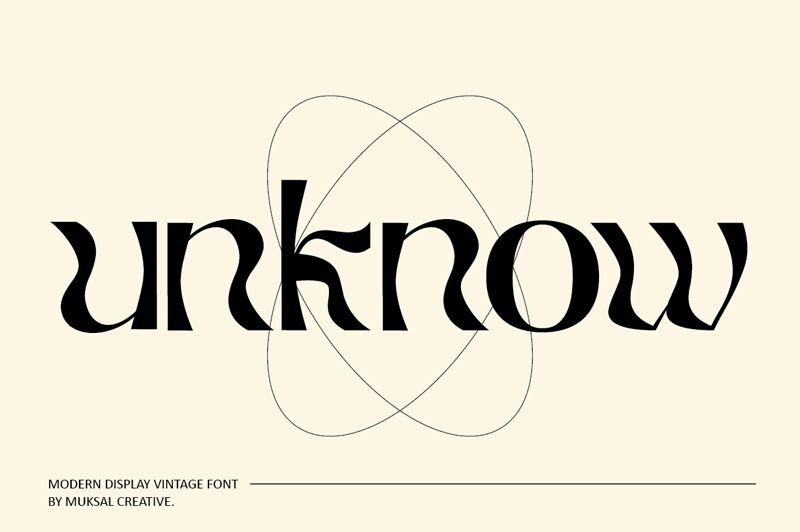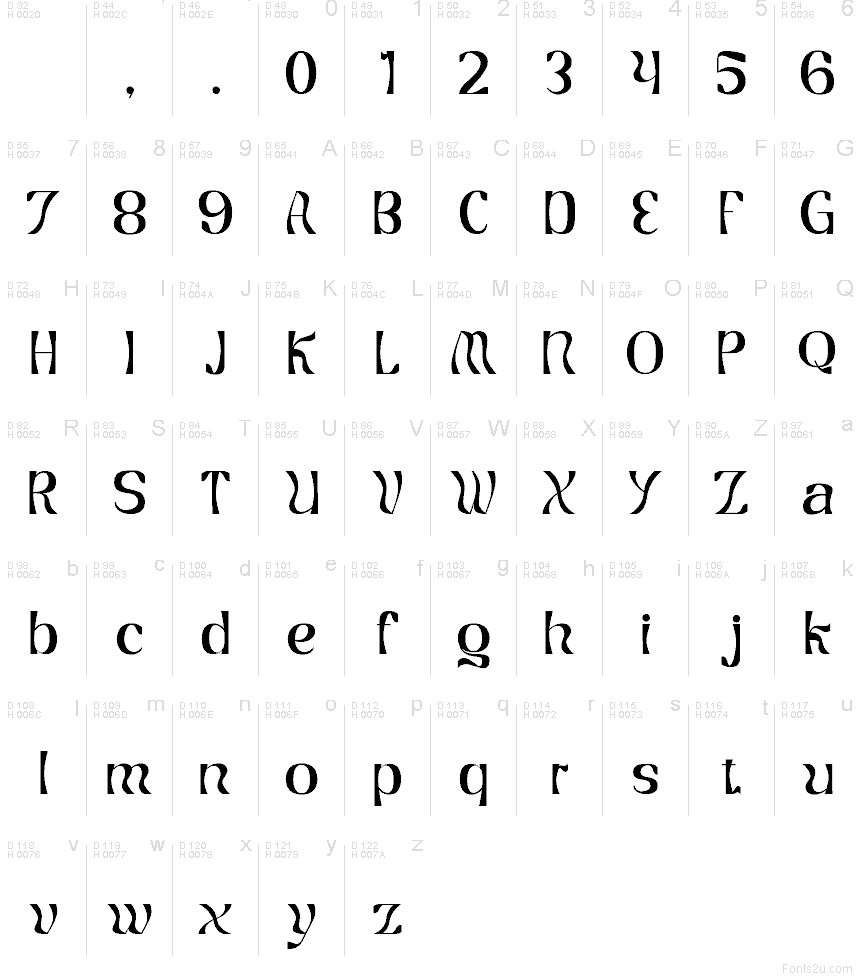
Unknow od Benya Muksal Craeative je bezplatné retro displejové písmo definované hlubokými výřezy, zúženými spoji a širokými tahy, díky nimž působí písmena spíše plynule než stroze. Jeho rytmus kolísá mezi úzkými krky a náhlými širokými křivkami, což designu dodává groovovou siluetu v plakátovém stylu, která zůstává dekorativní v celé sadě.
Tento pohyb dává krátkým nadpisům jasnou roli na přebalech alb, butikovém balení, brandingu kaváren, plakátech akcí i hlavičkách sociálních sítí. Zvláště přesvědčivě působí tam, kde rozvržení pomáhá trochu teatrální křivka, protože opakující se vzor rozšiřování a zužování vytváří jemnou ozvěnu 70. let namísto neutrálního výrazu.